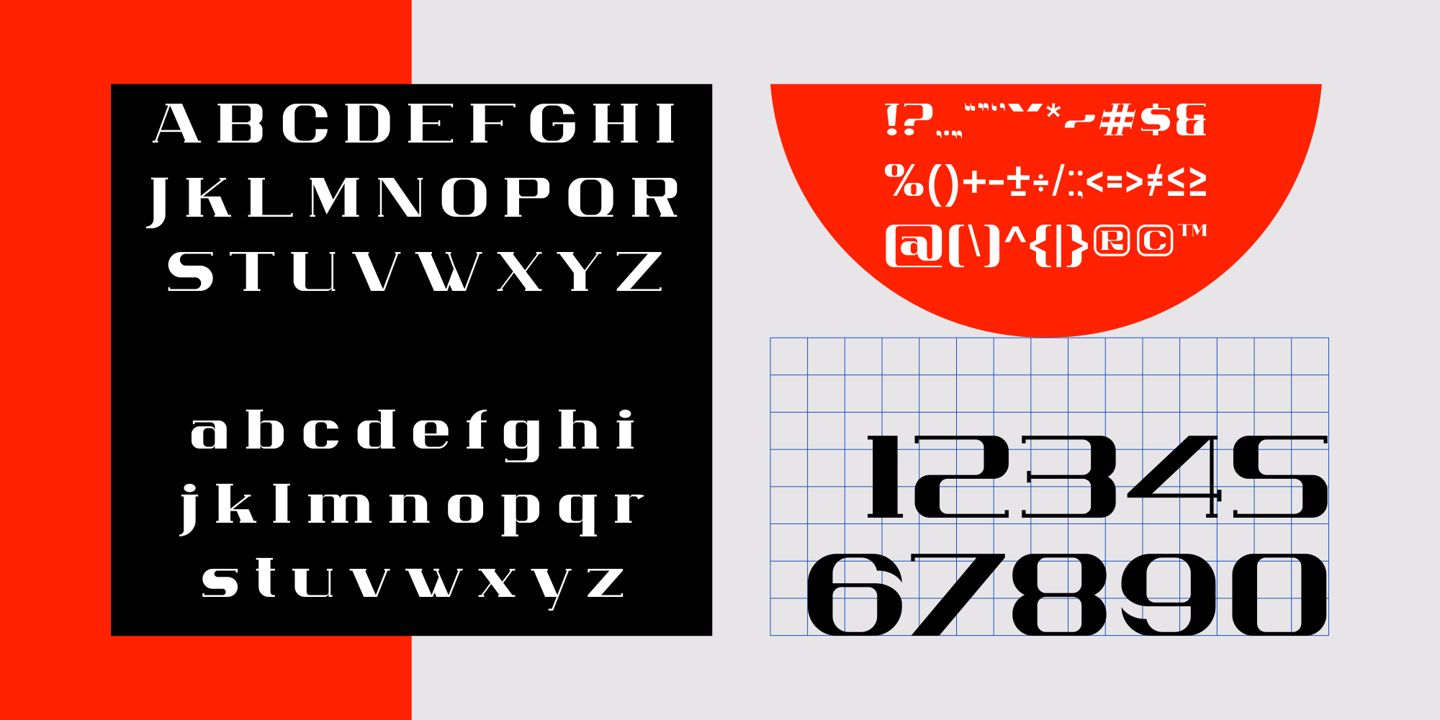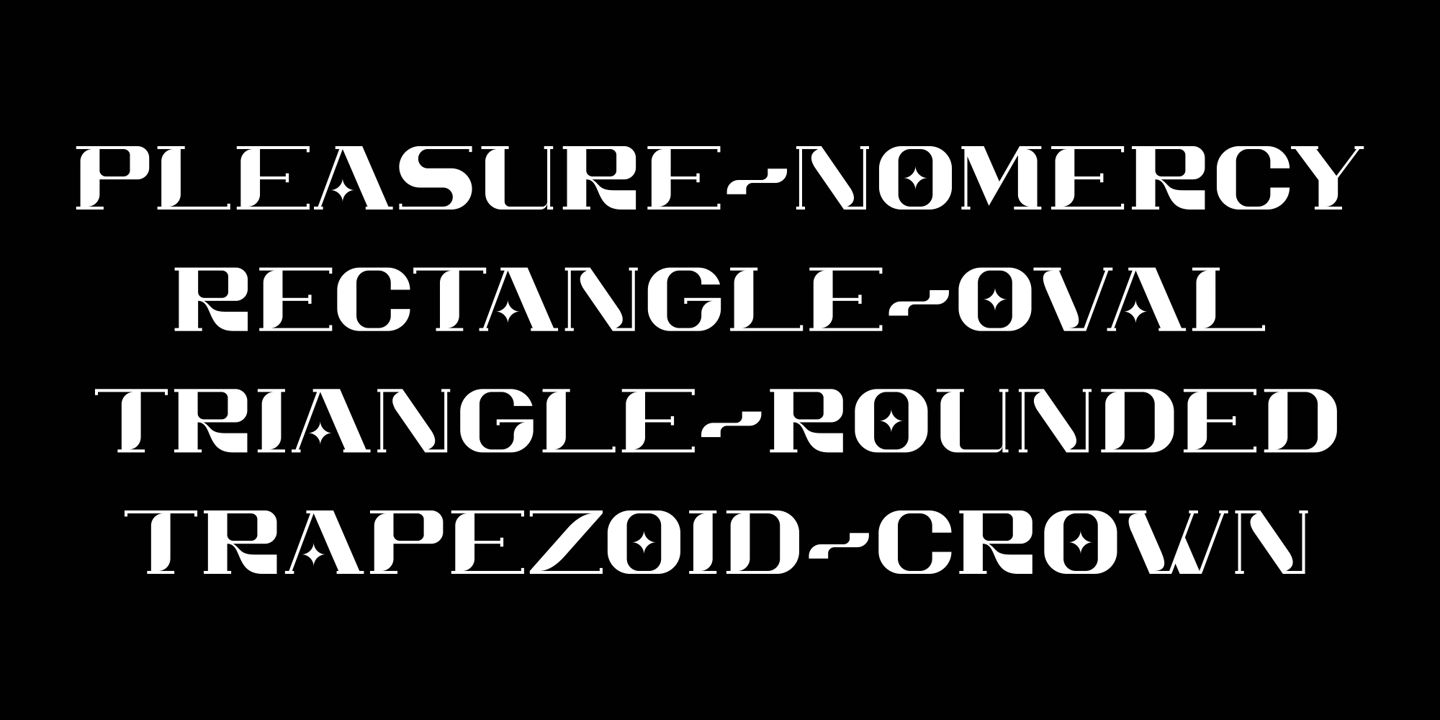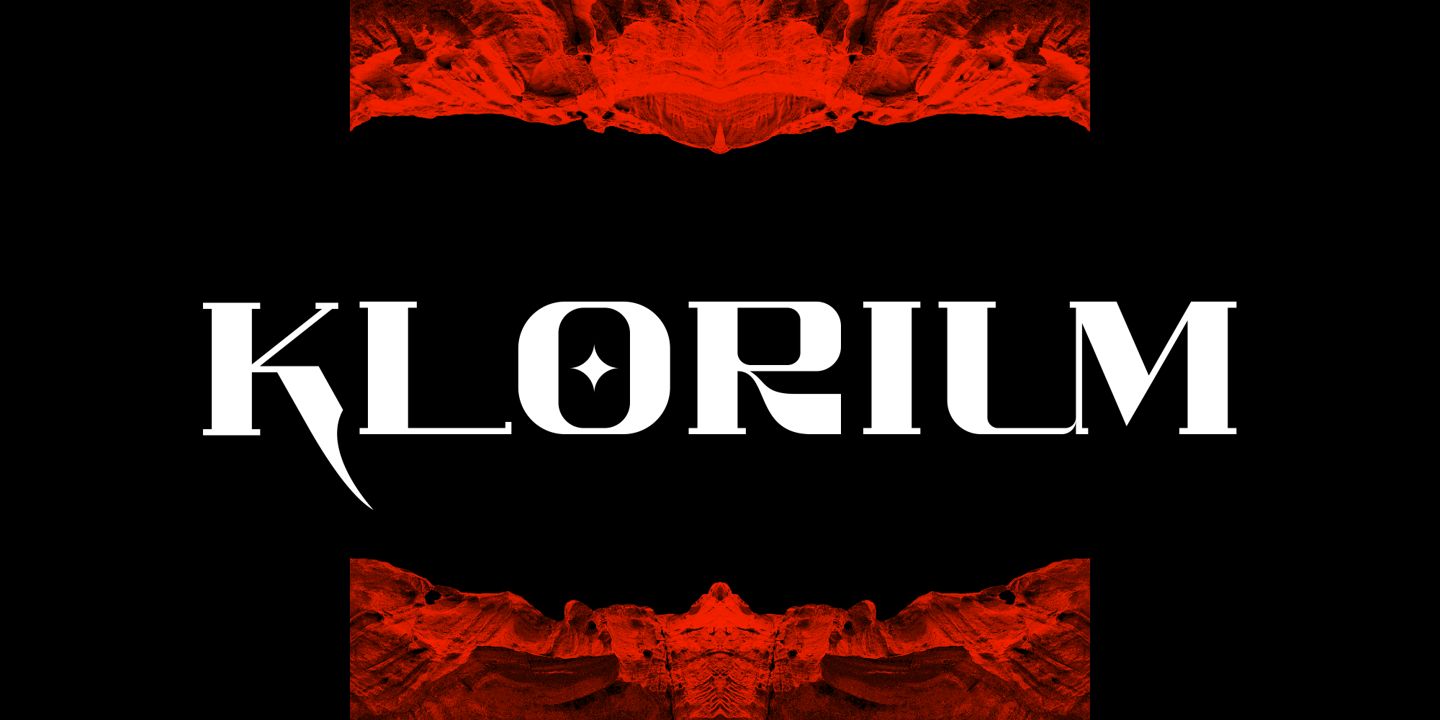
Homrich Font
Description de Homrich Font
Homrich est une police conçue par Fajar Ramadan, avec une combinaison de designs entre des thèmes de street wear urbains. Homrich est livré avec des styles, des alternatives, des ligatures et prend en charge les langues multilingues. Créez un logo unique et magnifique, utilisez-le comme une solution élégante pour la prochaine mise en page de votre magazine, ou choisissez Homrich pour tous les graphiques nécessitant un look élégant et élégant.